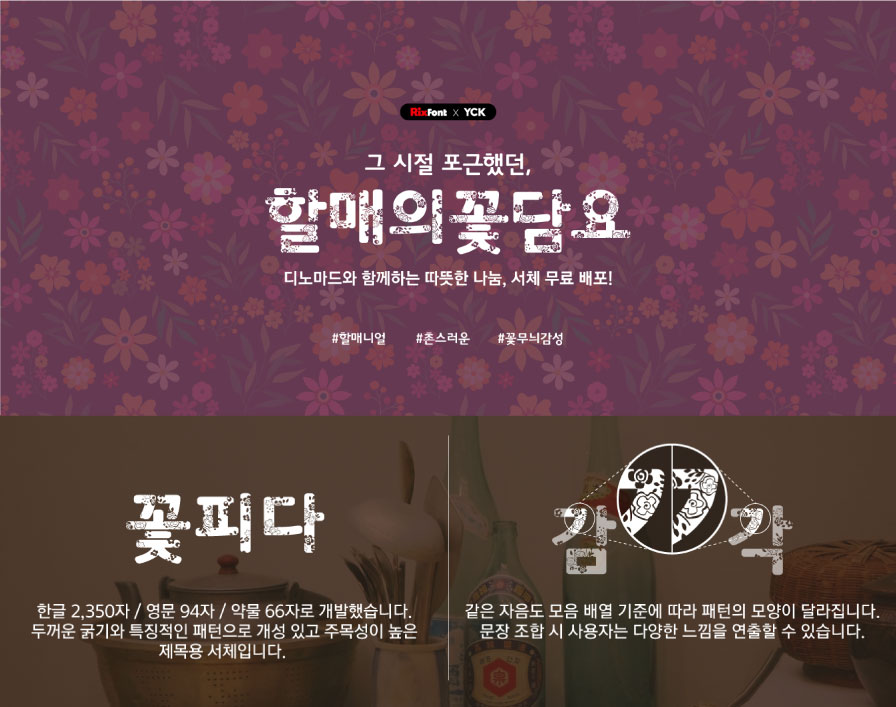
[RixFont X YCK] 그 시절 포근했던, Rix할매의꽃담요 서체 무료 나눔
디노마드와 함께하는 #따뜻한나눔 폰트 무료 배포 프로젝트
포근함으로 따스했던 그 시절을 기억하시나요?
빛 바랜 추억 속 할머니가 덮어주던 꽃무늬 이불처럼 촌스럽지만 따스한 감성 가득한 Rix할매의꽃담요 폰트를 개발, 무료로 배포합니다.